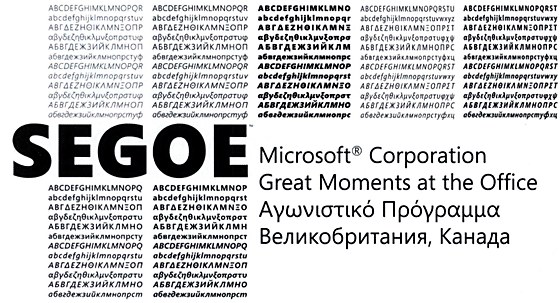
Segoe
Эта статья о шрифте. Для японского игрока в го см. Кенсаку Сегоэ. Для архитектора и градостроителя см. Ладислас Сегоэ.
Segoe (/ˈsяɡoʊ/ ВИДЕТЬ-гох ) это шрифт, или семейство шрифтов, наиболее известное своим использованием Microsoft. Компания использует Segoe в своих сетевых и печатных маркетинговых материалах, включая недавние логотипы для ряда продуктов. Кроме того, Segoe UI Подсемейство шрифтов используется многими приложениями Microsoft и может быть установлено приложениями (такими как Microsoft Office 2007 и Windows Live Messenger 2009 г. ). Он был принят в качестве шрифта операционной системы Microsoft по умолчанию, начиная с Виндоус виста, а также используется на outlook.com, Веб-служба электронной почты Microsoft. В августе 2012 года Microsoft представила свой новый набор корпоративных логотипов в Segoe, заменив логотип, который использовался в течение предыдущих 25 лет.[1]
Название Segoe является зарегистрированным товарным знаком Microsoft Corporation, хотя шрифт изначально был разработан Монотипия.
История
Segoe был разработан Стив Мэттесон во время его работы в Agfa Monotype. Лицензированный Microsoft для использования в качестве фирменного шрифта и шрифта пользовательского интерфейса, он был разработан, чтобы быть удобным и разборчивым. Маттесон создал ряд шрифтов и курсивов с гуманист Чувствовать.
Лицензионные споры
В 2004 году Microsoft зарегистрировала определенные шрифты Segoe и Segoe Italic в качестве оригинальных шрифтов с Евросоюз торговая марка и дизайнерское бюро. Немецкая фабрика шрифтов Линотип протестовали, ссылаясь на сходство Segoe UI с лицензированным Фрутигер семейство шрифтов. В своем заявлении в ЕС Microsoft заявила, что Linotype не удалось доказать, что он продавал Фрутигер и Frutiger Next до 2004 г.
ЕС отклонил эти претензии, и в феврале 2006 г. ЕС отменил регистрацию Microsoft.[2] Microsoft не обжаловала это решение. Microsoft по-прежнему владеет патентами США на дизайн различных шрифтов на основе Segoe.
В тот же период, в конце 2004 г., после шести лет работы в корпорации Agfa, активы Monotype были приобретены TA Associates и компания была зарегистрирована как Монотипия изображения. Позже, в августе 2006 г., Монотипия изображения приобрел линотип.[3] Таким образом, в конце 2006 года Linotype, компания, которая оспорила законность патентов Microsoft на Segoe, стала дочерней компанией, полностью принадлежащей Monotype, компании, которая первоначально предоставила лицензию на Segoe Microsoft.
Наиболее явные различия (сверху вниз) Segoe UI, Frutiger и Segoe
Некоторые буквы имеют совершенно разные формы в Segoe UI и Frutiger, что отражает различное предполагаемое использование Segoe UI: отображение экрана с низким разрешением, а не вывески аэропорта (Frutiger).
Однако Ульрих Штиль утверждает, что многие из этих различий были введены в более поздних версиях Segoe UI — более ранние версии Segoe UI были ближе к Frutiger.[4][5]
7 июня 2005 г. Scala, компания по производству электронных вывесок (не имеющая отношения к шрифту FF Scala ), объявленный[6] что Segoe удаляется из продукта InfoChannel «из-за проблем с лицензированием». Scala заменила Segoe на Bitstream Vera шрифты.
В ноябре 2005 года Саймон Дэниелс, руководитель программы типографической группы Microsoft, заявил, что «оригинальные шрифты Segoe не были созданы для Microsoft или компанией Microsoft. Это был существующий дизайн Monotype, который мы лицензировали, расширили и настроили для соответствия требованиям различных процессы, приложения и устройства «.[7]
В апреле 2006 года представитель Microsoft по связям с общественностью, попросивший не называть его имени, заявил:
Segoe был оригинальным дизайном, разработанным Agfa Monotype (теперь Monotype Imaging) в 2000 году.
В 2003 году мы приобрели оригинальные шрифты Segoe и использовали их для разработки расширенного семейства шрифтов, сохранивших название Segoe. Многие из этих новых шрифтов получили патентную защиту в США. Segoe не произошел от Frutiger. Microsoft также имеет актуальную лицензию, которая позволяет нам распространять определенные шрифты Frutiger в связи с продуктами Microsoft, включая Office и Windows. Между Segoe и Frutiger есть явные различия. Кроме того, в отличие от шрифтов-клонов, семейство шрифтов Segoe не является метрически совместимым с Frutiger, поэтому не может использоваться в качестве замены.[8]
В соответствии с законом США об авторском праве абстрактные формы букв функциональных текстовых шрифтов не могут быть защищены авторским правом; только код компьютерного программирования в шрифте защищен авторскими правами. Это делает возможным производство и распространение клонированных шрифтов.
Ранняя версия Segoe, возможно, ознакомительная, была включена в некоторые версии SuSE Linux, но больше не входит в состав этой операционной системы.
Segoe UI
Пользовательский интерфейс Segoe является членом семейства Segoe, используемого в продуктах Microsoft для текста пользовательского интерфейса, а также для некоторых интерактивных вспомогательных материалов для пользователей, предназначенных для повышения единообразия того, как пользователи видят весь текст на всех языках. Он отличается от своего предшественника. Тахома и OS X шрифт пользовательского интерфейса Люсида Гранде округлыми буквами. Segoe UI был разработан Monotype Imaging.[9]
Segoe UI Variable решает эту проблему с помощью новой версии Segoe, которая использует технологию изменяемых шрифтов, чтобы динамически обеспечивать отличную читаемость при очень малых размерах и стиль при больших размерах.